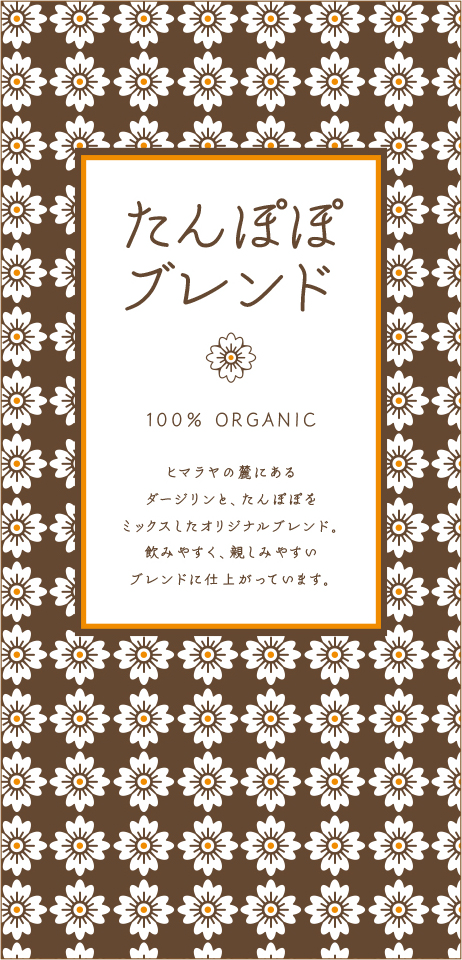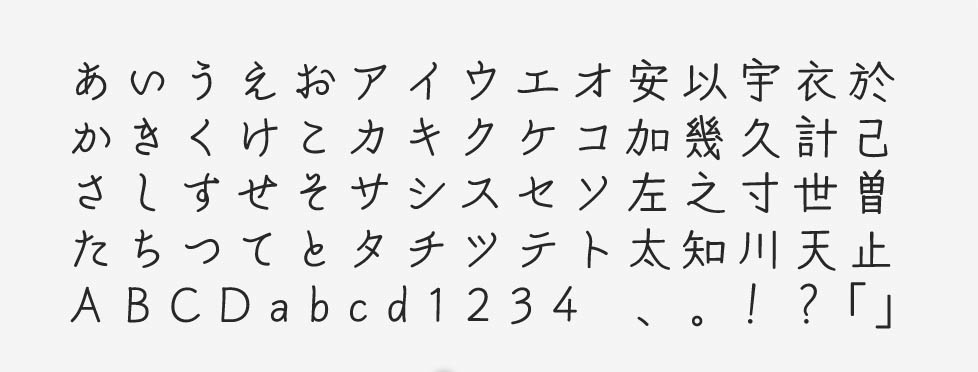
「白妙 オールド」について
白妙 オールドは2022年に提供が開始されたフォントです。手書き文字の要素を取り入れてデザインされています。同時リリースの白妙と漢字は共通ですが、白妙のかな文字がさらりとした軽やかな印象であるのに対し、白妙 オールドのかな文字は筆の運びが残された、よりレトロな表情です。
「白妙 オールド」の特徴
白妙 オールドの漢字は、やや長体ぎみの字面に仕上げられています。かな文字は柔らかな印象で、温かみも感じさせるフォントです。LウエイトとMウエイトがあり、見出しからキャプションまで、さまざまな箇所で使用できます。
このフォントは、作例のようなパッケージや書籍やポスターなどのほか、挨拶状などにも使いやすい雰囲気です。文字列を自然な流れで読み進めることができ、優しい気持ちも表現しやすいフォントと言えるでしょう。
白妙 オールドの文字は線のカーブの特徴が強く、短めのテキスト、コピー、タイトルで使うと面白い印象を与えます。極端な長文を読ませるようなシーンにはあまり向いていないかもしれません。文字組みが難しいフォントですが、うまくハマれば効果は絶大です。
書籍、雑誌、パンフレット、商品パッケージ、挨拶状